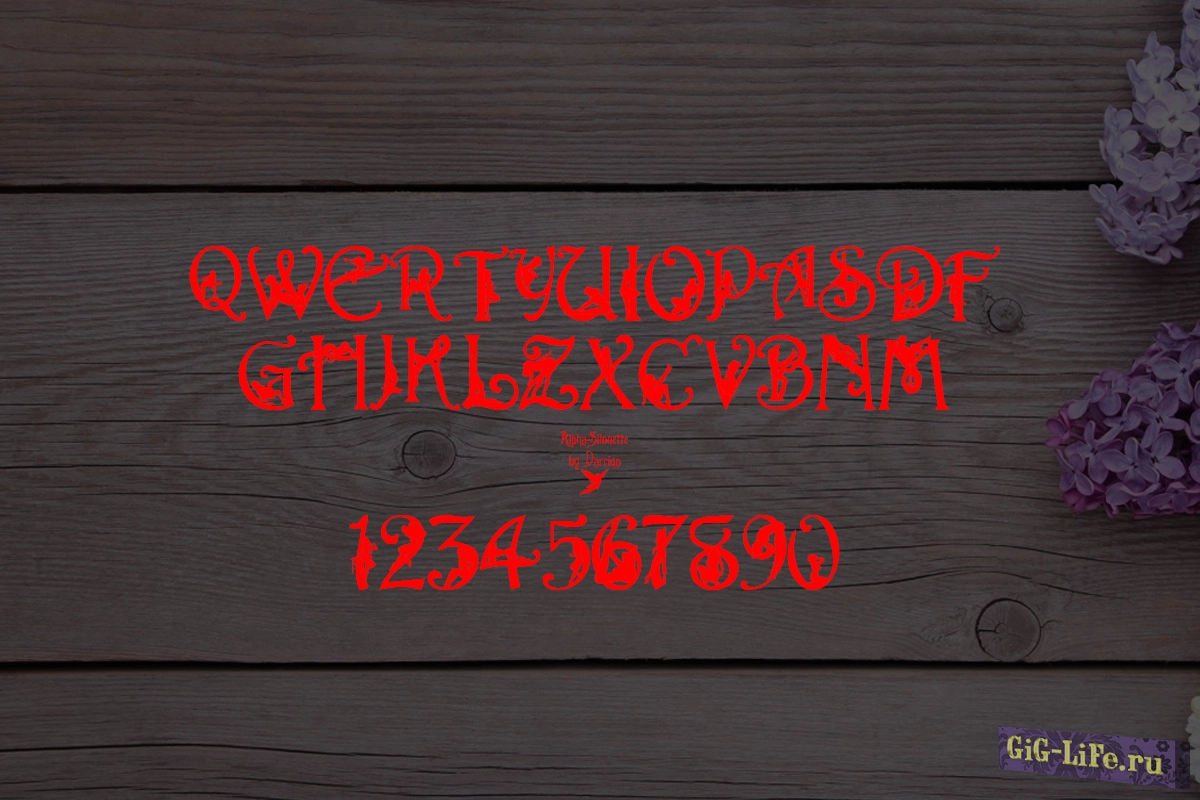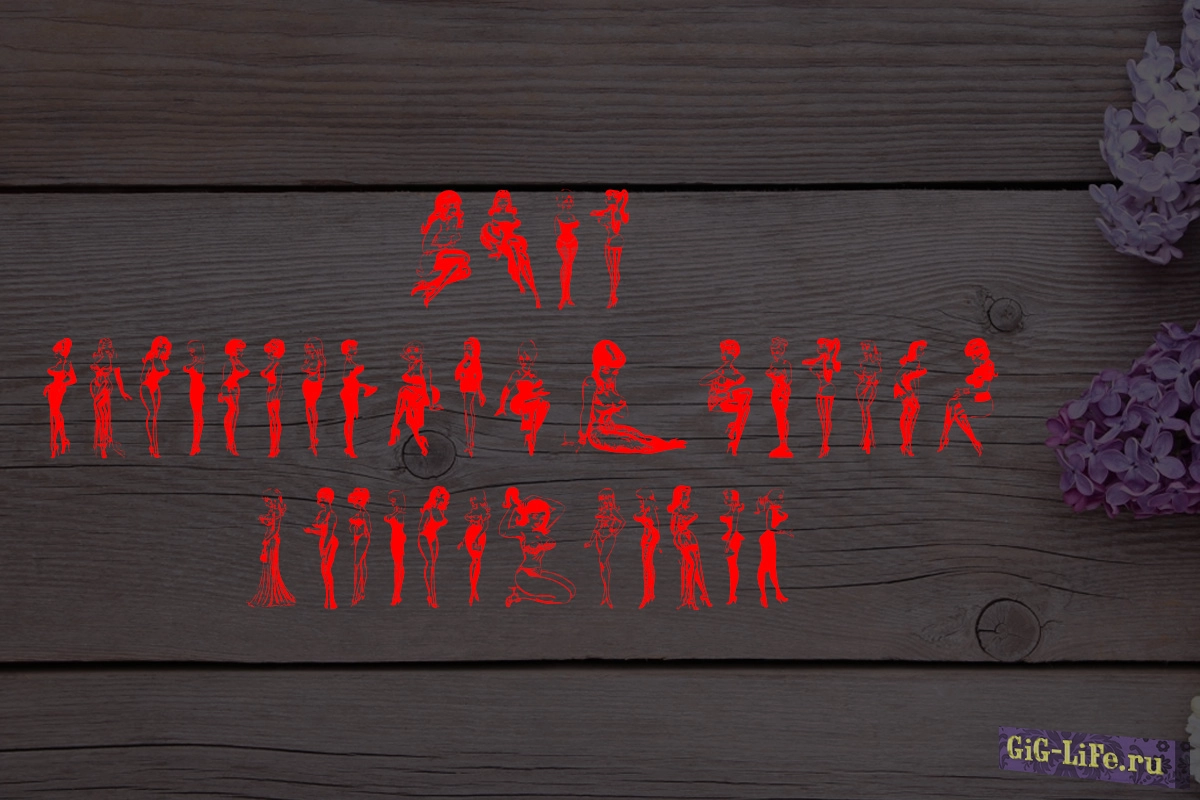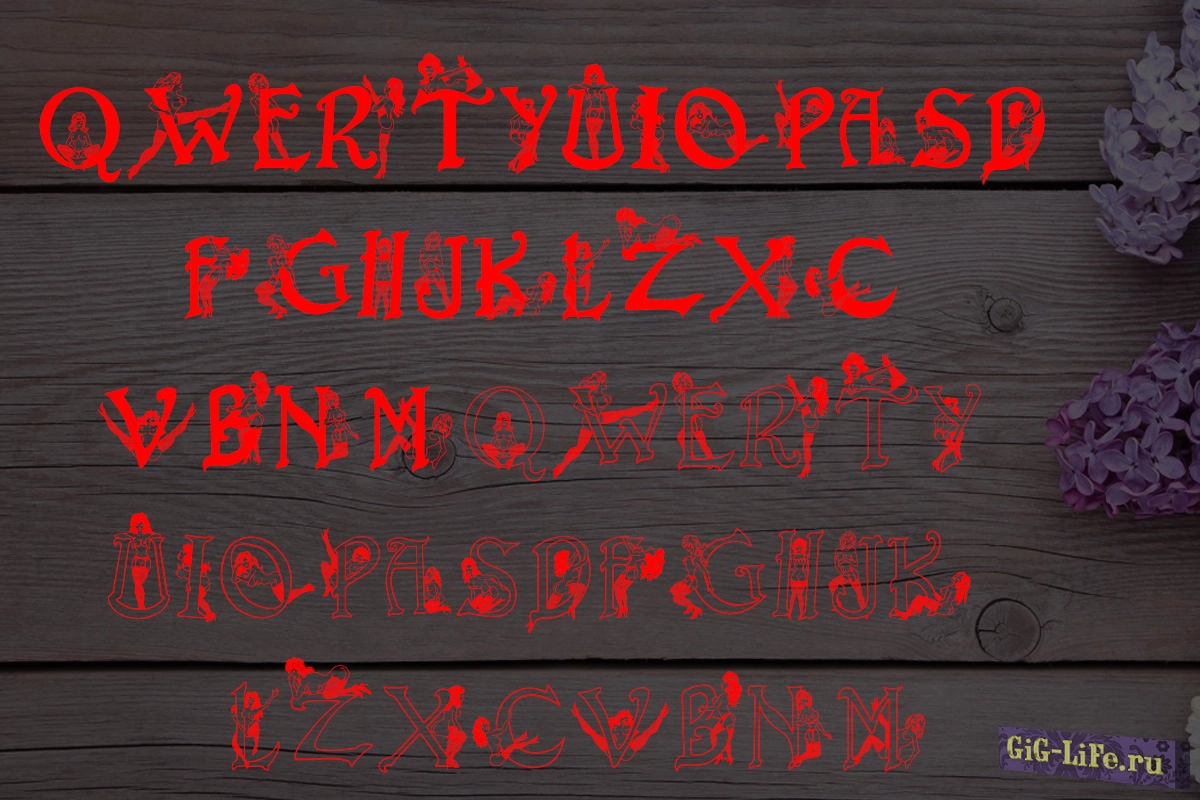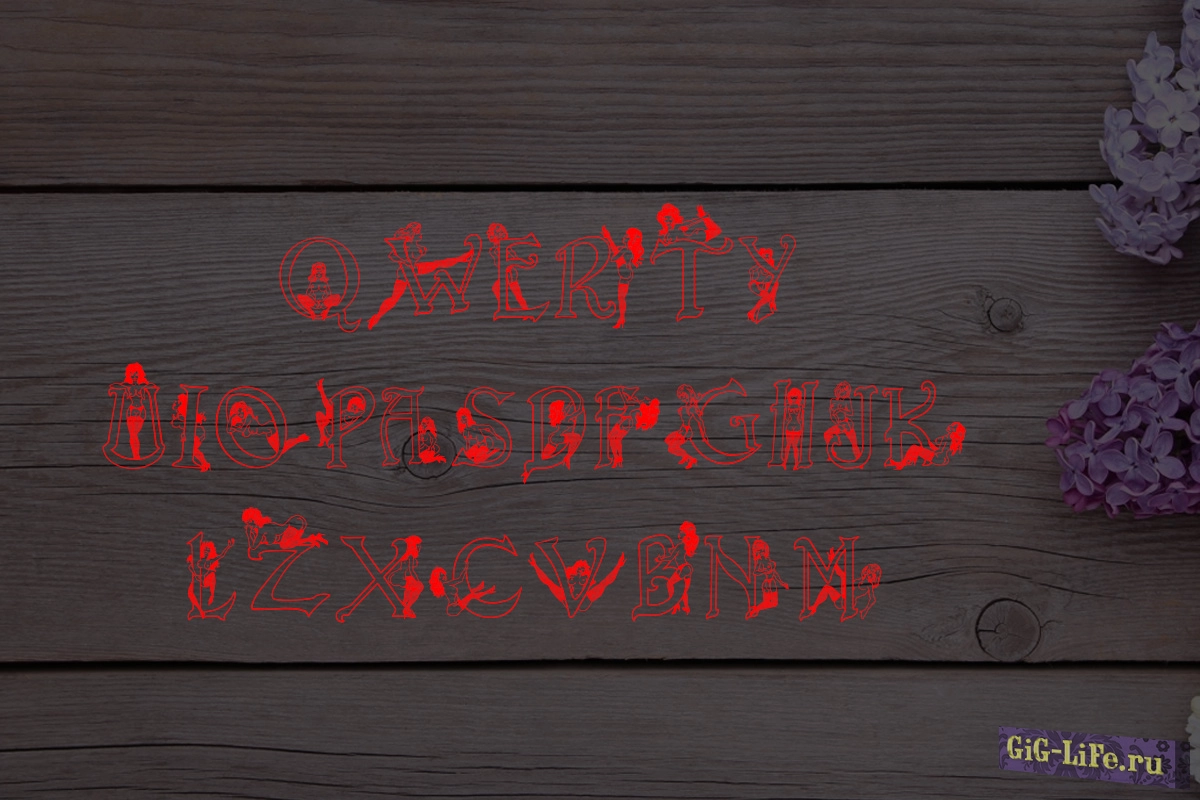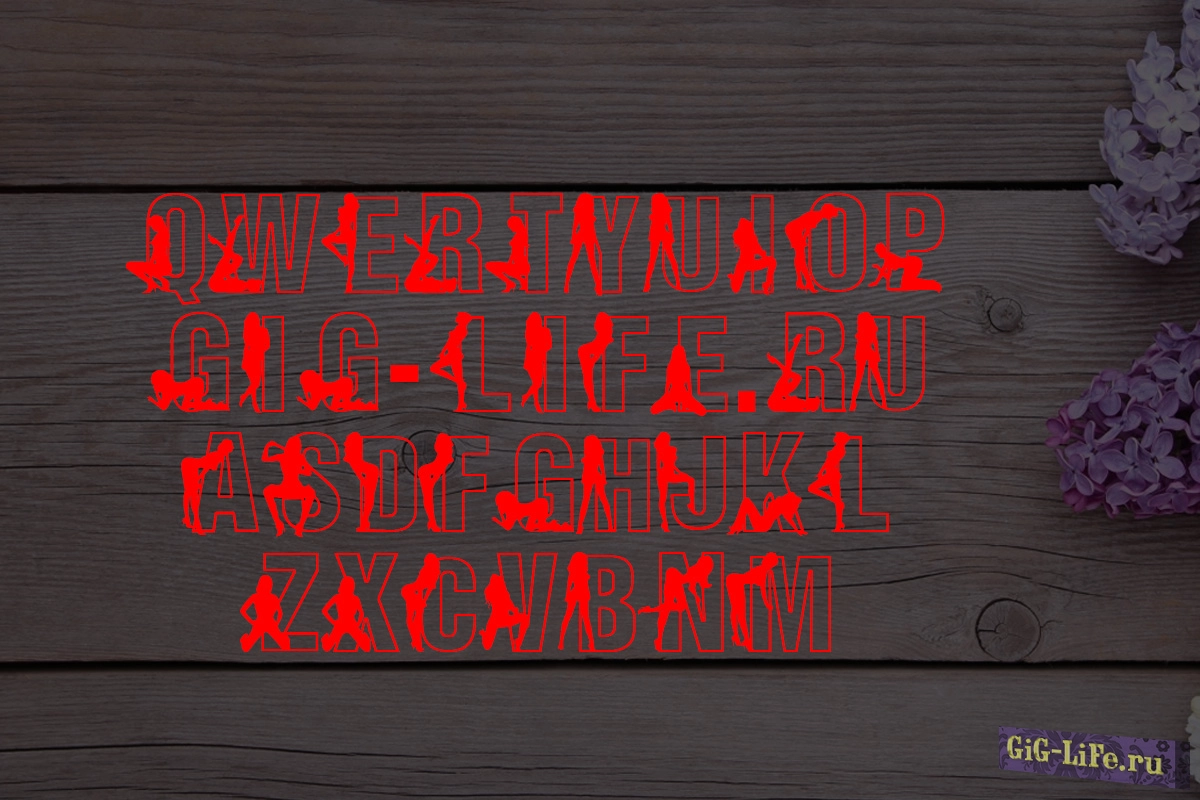
FuzzyCootie является эротическим шрифтом, разработанным специально для использования в Photoshop и других творческих проектах. Он представляет собой английский шрифт, который придает особую сексуальность вашим работам.